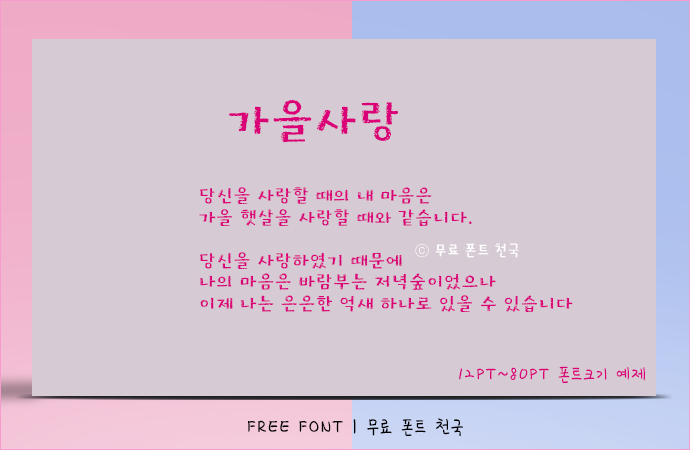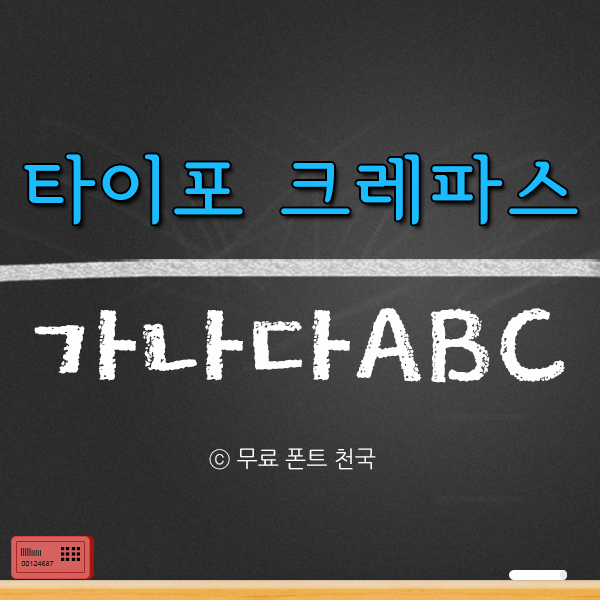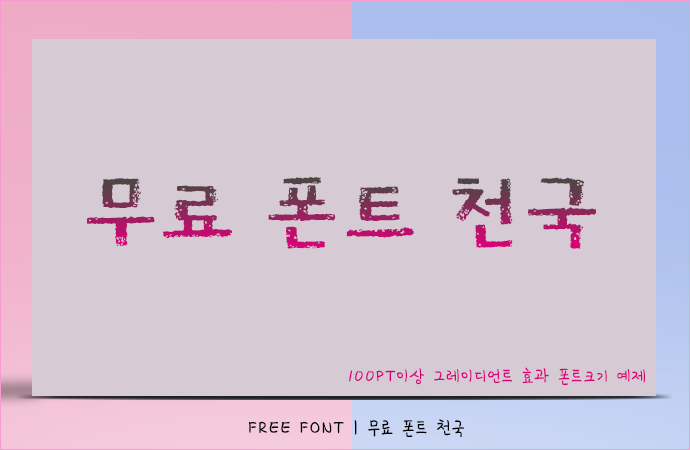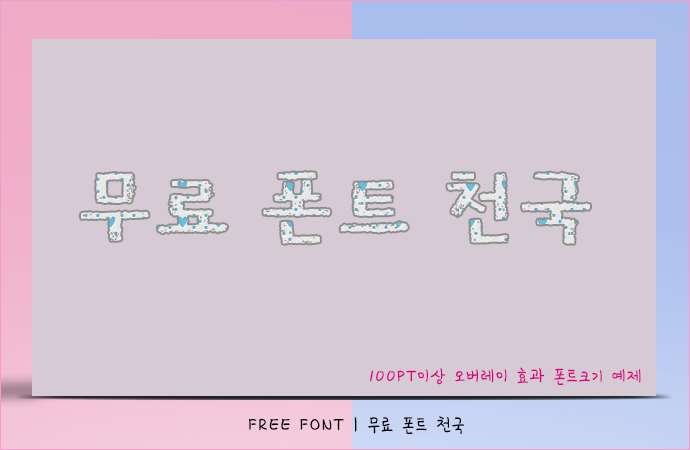
어린 아이의 감수성이 풍겨나는 타이포 크레파스 폰트
밋밋하고 단순한 글씨체를 어린 아이의 감수성이 풍겨나는 서체로 바꿔주는 타이포 크레파스 무료폰트입니다. 거칠고 크레파스로 작성한 듯한 느낌을 쉽고 편리하게 만들 수 있습니다. 본 폰트는 개인이 비상업적용도로 사용 가능하며, 상업적인 용도로 사용할 경우 별도의 라이센스를 구매하셔야 합니다.
타이포 크레파스 폰트 # 미리보기
타이포 크레파스 폰트, 12~80PT 크기로 적용한 효과
타이포 크레파스 폰트, 100PT 크기 이상으로 작업한 오버레이 효과
타이포 크레파스 폰트, 100PT 크기 이상으로 작업한 그레이언트 효과